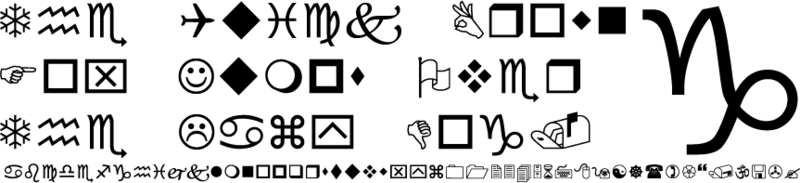
杂锦符号(Dingbat)
导语杂锦符号(Dingbat)俗称杂锦字体,本来是印刷品之中使用的装饰及图形符号。在计算机被用来制作印刷刊物后,印刷业界便制造了各种杂锦字体,最著名的是Adobe的Zapf Dingbats字体。Zapf Dingbats 字符集
杂锦符号(Dingbat)俗称杂锦字体,本来是印刷品之中使用的装饰及图形符号。在计算机被用来制作印刷刊物后,印刷业界便制造了各种杂锦字体,最著名的是Adobe的Zapf Dingbats字体。
Zapf Dingbats 字符集
微软于Windows 3.1操作系统之中,提供了Wingdings杂锦符号字体。而微软于1997年之后发行的操作系统,再加入了Webdings杂锦符号字体。
图:Wingdings杂锦符号字体
图:Webdings杂锦符号字体
图:Webdings 2杂锦符号字体
图:Webdings 3杂锦符号字体
Unicode的U+2700至U+27BF,亦收录了一些杂锦字体。
Unicode的U+2700-U+27BF 字符集